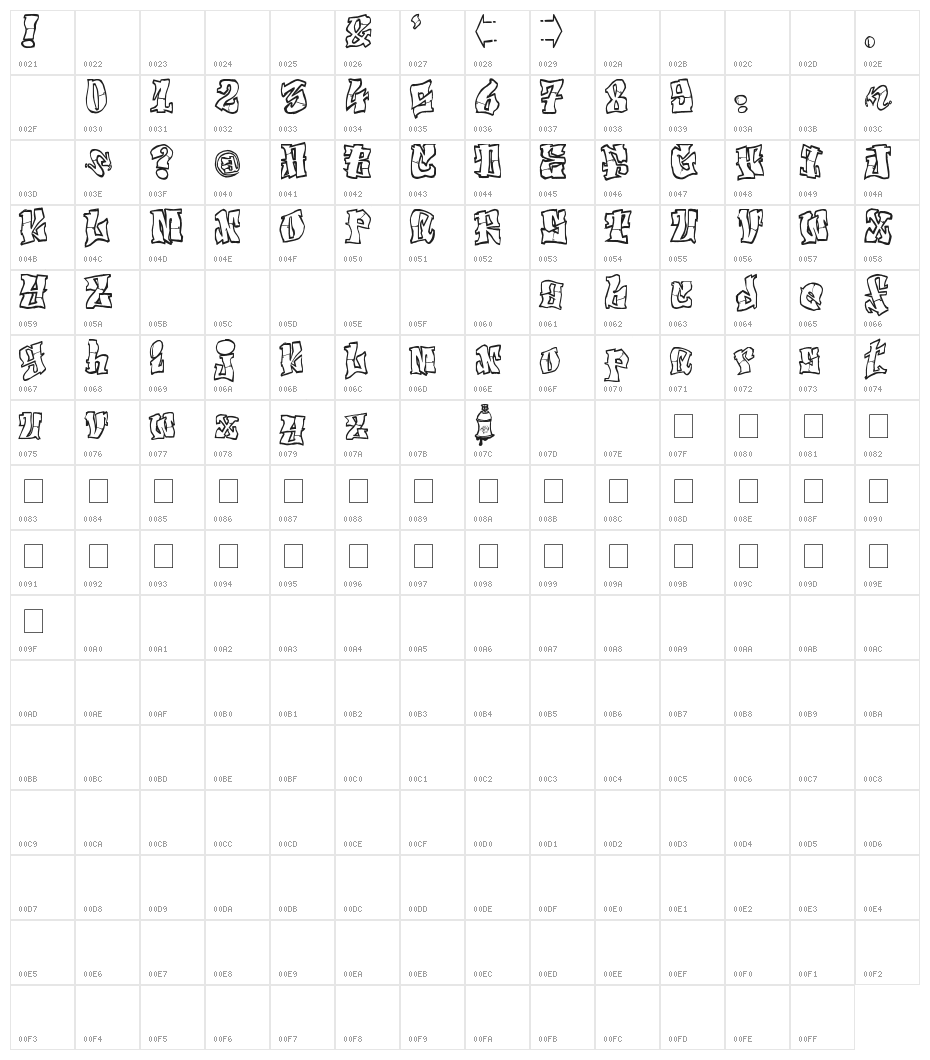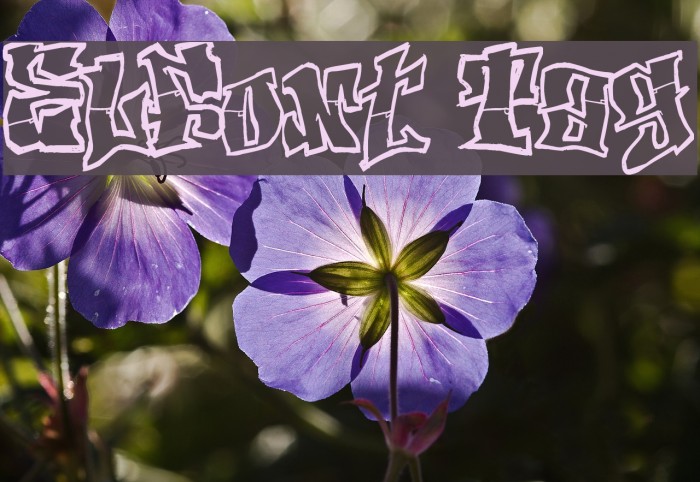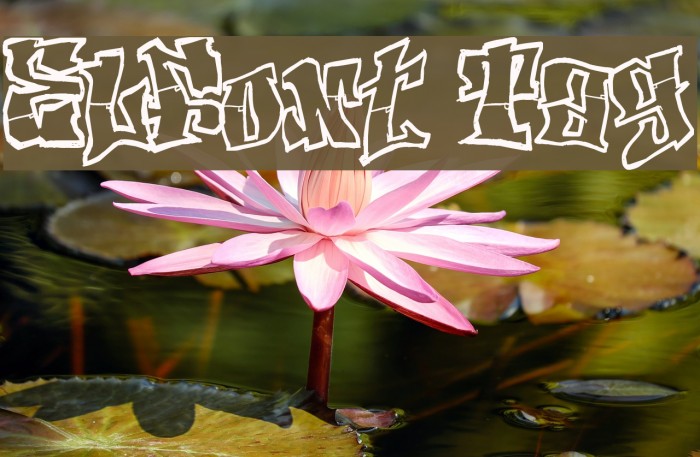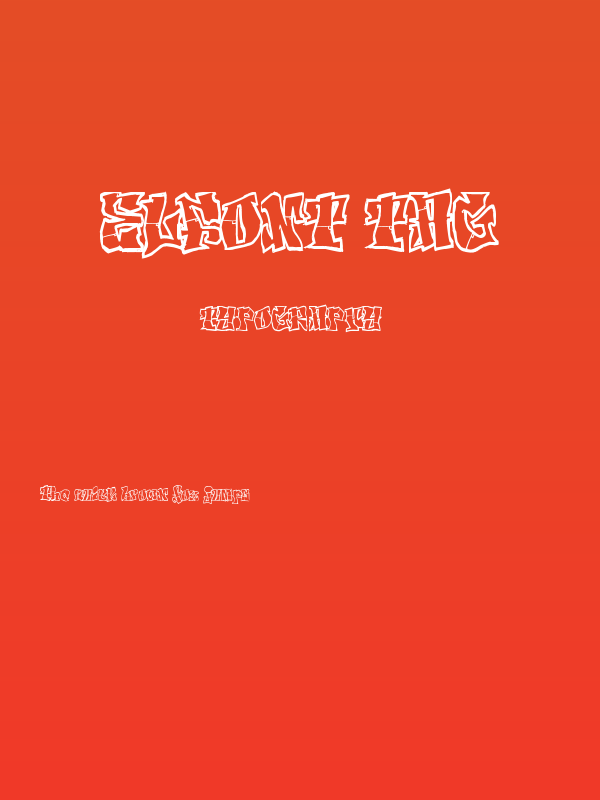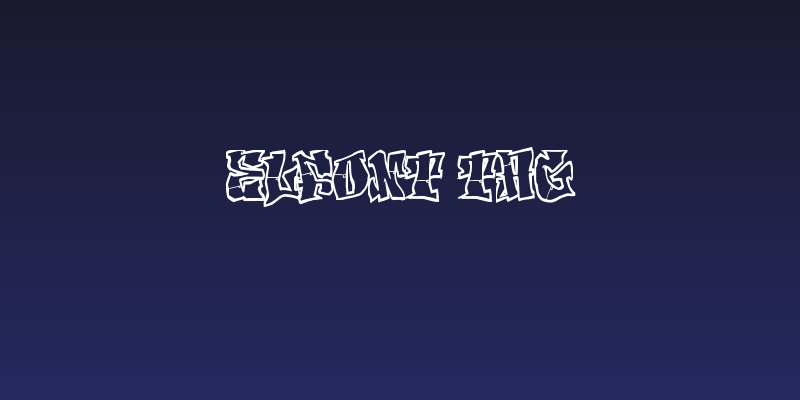
ElFont Tag Font
| Stile generale | Urban, Graffiti, Energetic |
| Progetti proposti | Ideal for street art designs, urban-themed posters, music album covers, and edgy branding projects. |